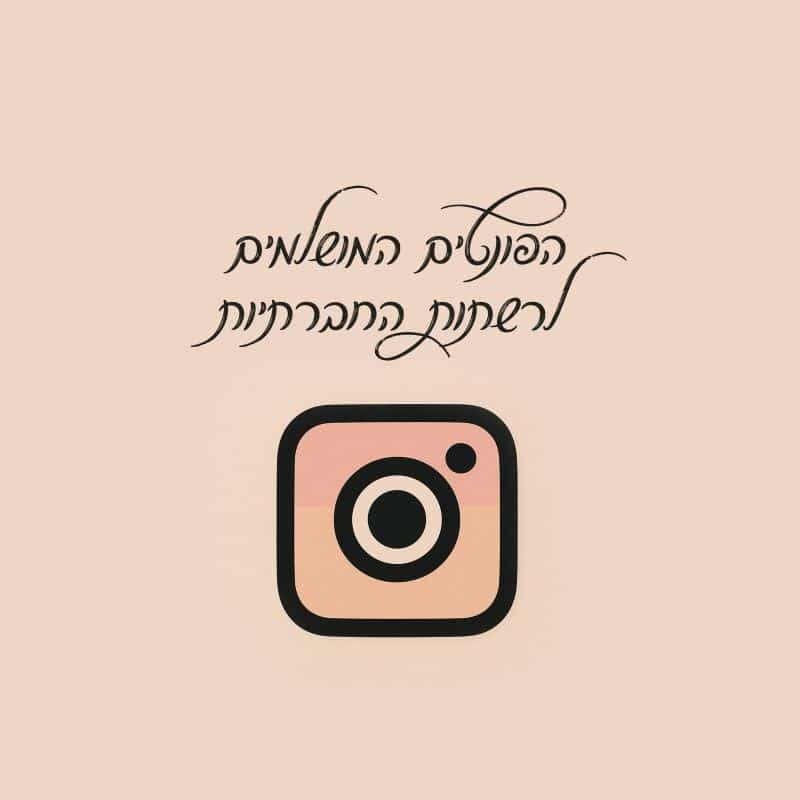
בעידן שבו התוכן החזותי משחק תפקיד מרכזי בשיווק ובנראות של מותגים דיגיטליים, בחירת הפונט המתאים היא לא פחות קריטית מהעיצוב הגרפי עצמו.
הפונט שבו בוחרים להשתמש יכול לשדר רגש, להעביר אווירה, ליצור וייב, וממש להשפיע על רמת המעורבות של העוקבים.
בין אם מדובר בפוסט של תמונות קרוסלה לאינסטגרם, פוסט טקסט לפייסבוק או סרטון ויראלי בטיקטוק, השימוש בפונט הנכון יכול לעשות את כל ההבדל.
אז איך בוחרים את הפונטים המתאימים והמדויקים ביותר לרשתות החברתיות? בואו נצלול לתוך עולם הטיפוגרפיה הדיגיטלית ונלמד איך להשתמש בה נכון. צפו להפוך לאלופים!
כשבוחרים פונטים בעברית, חשוב לשים לב להתאמה בין הסגנון של הפונט לבין הזהות החזותית של המותג הספציפי. למשל, מותגים שמכוונים לקהל צעיר יעדיפו מן הסתם פונטים קלילים ודינמיים, בעוד שמותגים יוקרתיים יבחרו בדרך כלל בפונטים אלגנטיים ומינימליסטיים.
פונטים המשדרים קלילות או להיפך, רשמיות, עשויים להשפיע על איך שהמותג נתפס בעיני הקהל. מלבד זאת, יש לזכור שהקריאות היא מרכיב מכריע ביותר.
פונטים בעלי קווים נקיים וברורים יתאימו יותר לכותרות ופוסטים קצרים, בעוד שפונטים עם קישוטים או אותיות צפופות עשויים להקשות על קריאה מהירה – אולי הדבר הכי קריטי בעולם הרשתות החברתיות.
אחד הטרנדים היום הוא פונט כתב יד, המשדר תחושה אישית וא-פורמלית. מותגים שמשתמשים בפונטים מסוג זה מצליחים ליצור יותר חיבור רגשי עם הקהל שלהם, כיוון שהטיפוגרפיה מחקה את הכתיבה הטבעית.
הסגנון מתאים במיוחד לעסקים קטנים, בלוגים אישיים ומותגים שמדברים בגובה העיניים עם העוקבים שלהם.
ניתן לראות שימוש נרחב בפונטים אלו בעולמות כמו אופנה, מזון ואפילו ברשתות חברתיות של יועצים עסקיים, המעוניינים ליצור חיבור אישי יותר עם הקהל שלהם.
עם זאת, יש להשתמש בפונט זה במידה, שכן שימוש יתר עלול לפגוע בקריאות ולהפוך את העיצוב לפחות מקצועי.
כדאי להימנע משימוש ביותר מדי סוגי פונטים שונים בעיצוב אחד כדי לשמור על אחידות ומראה מקצועי.
אם אתם מחפשים פונטים מומלצים בעברית לרשתות החברתיות, כדאי להתמקד בכמה פרמטרים:
בין אם מדובר בפוסטים יומיומיים או בקמפיין גדול, פונטים הם חלק בלתי נפרד מהשפה החזותית של המותג שלכם.
בחירה נכונה של פונטים תשפר את הקריאות, תחזק את המסר ותגרום לעוקבים שלכם להרגיש מחוברים יותר למותג.
יש להתחשב בזהות המותג, במסר שרוצים להעביר ובקריאות הפונט במובייל ובמחשב.